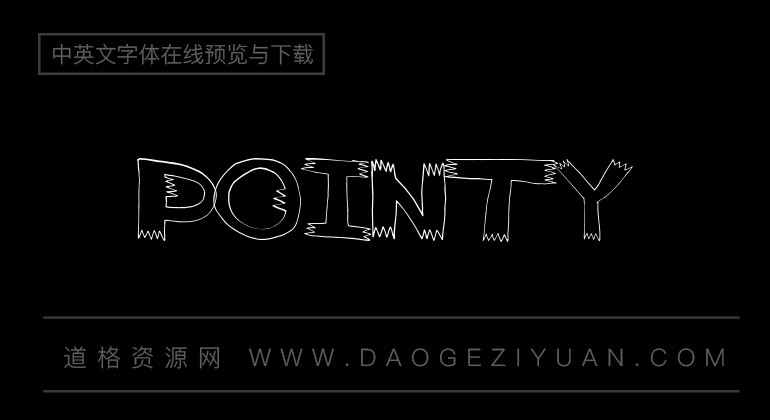
Pointy 是一款非常特别的字体,它的特点是在每一个字母的四个角上都会有一个尖角,使得字体看起来十分有趣。它具有极高的可读性,适合用于标题,logo等设计中。此外,Pointy 字体也有很多不同的字体样式,可以满足各种不同的需求。内容介绍
Pointy是一款非常不错的手写艺术字体,具有很好的视觉感,适合于文化类的宣传设计、商业类品牌的广告和产品包装设计以及个性化文字排版等较多场景。